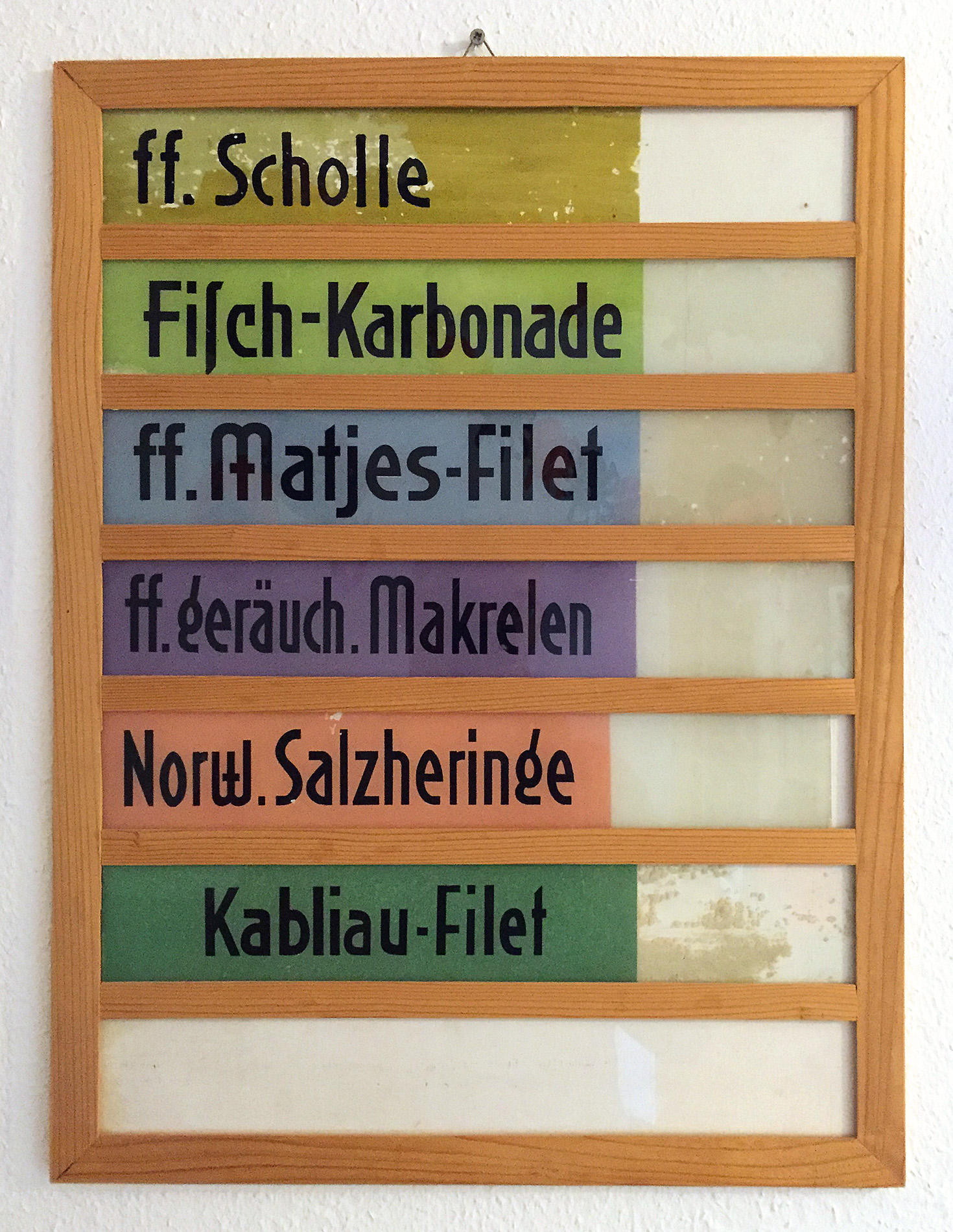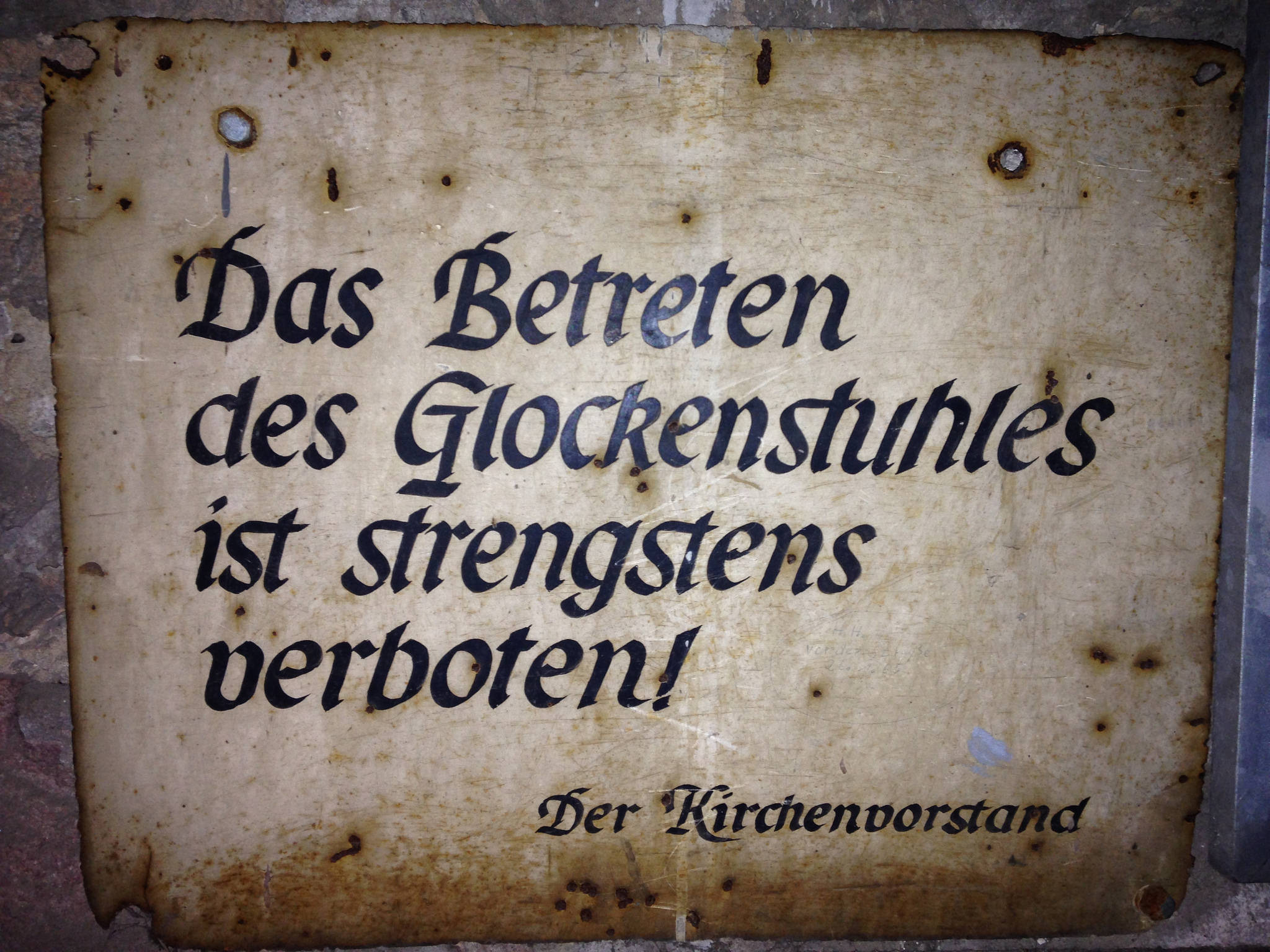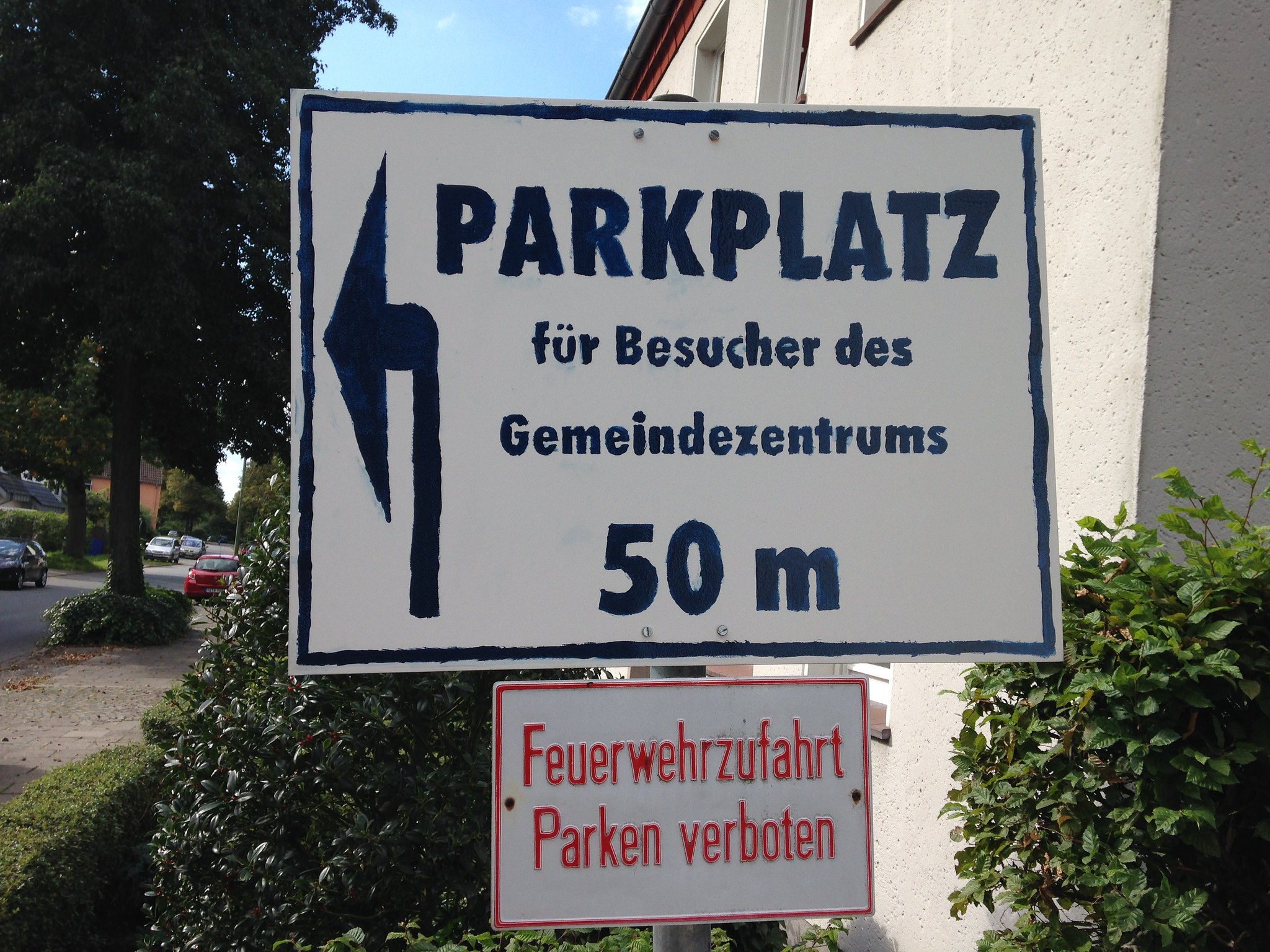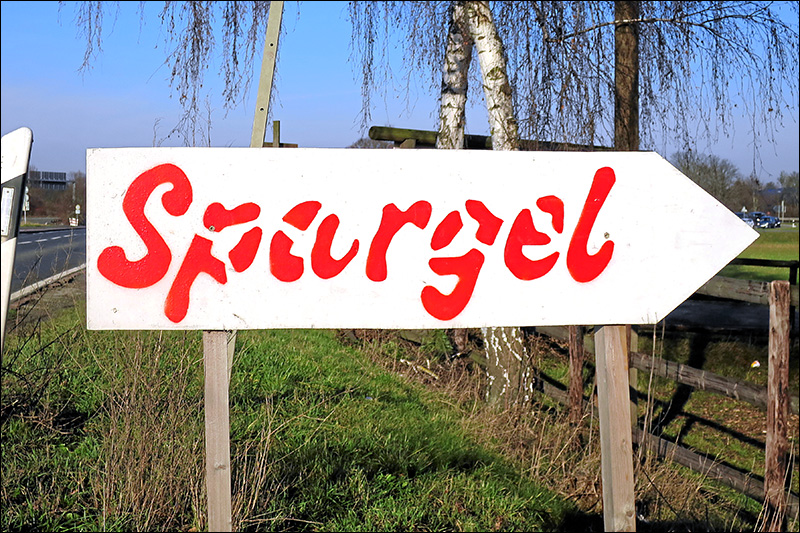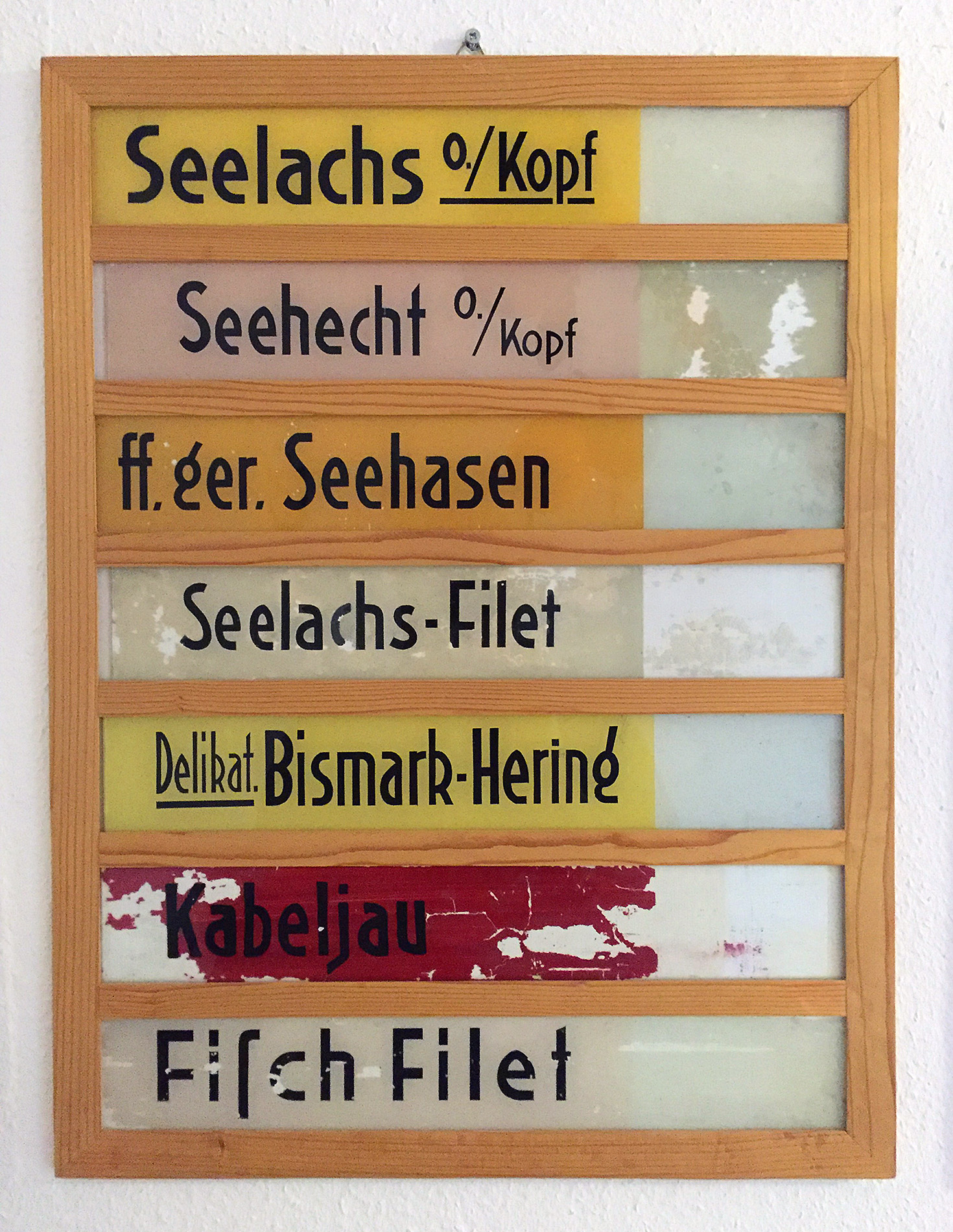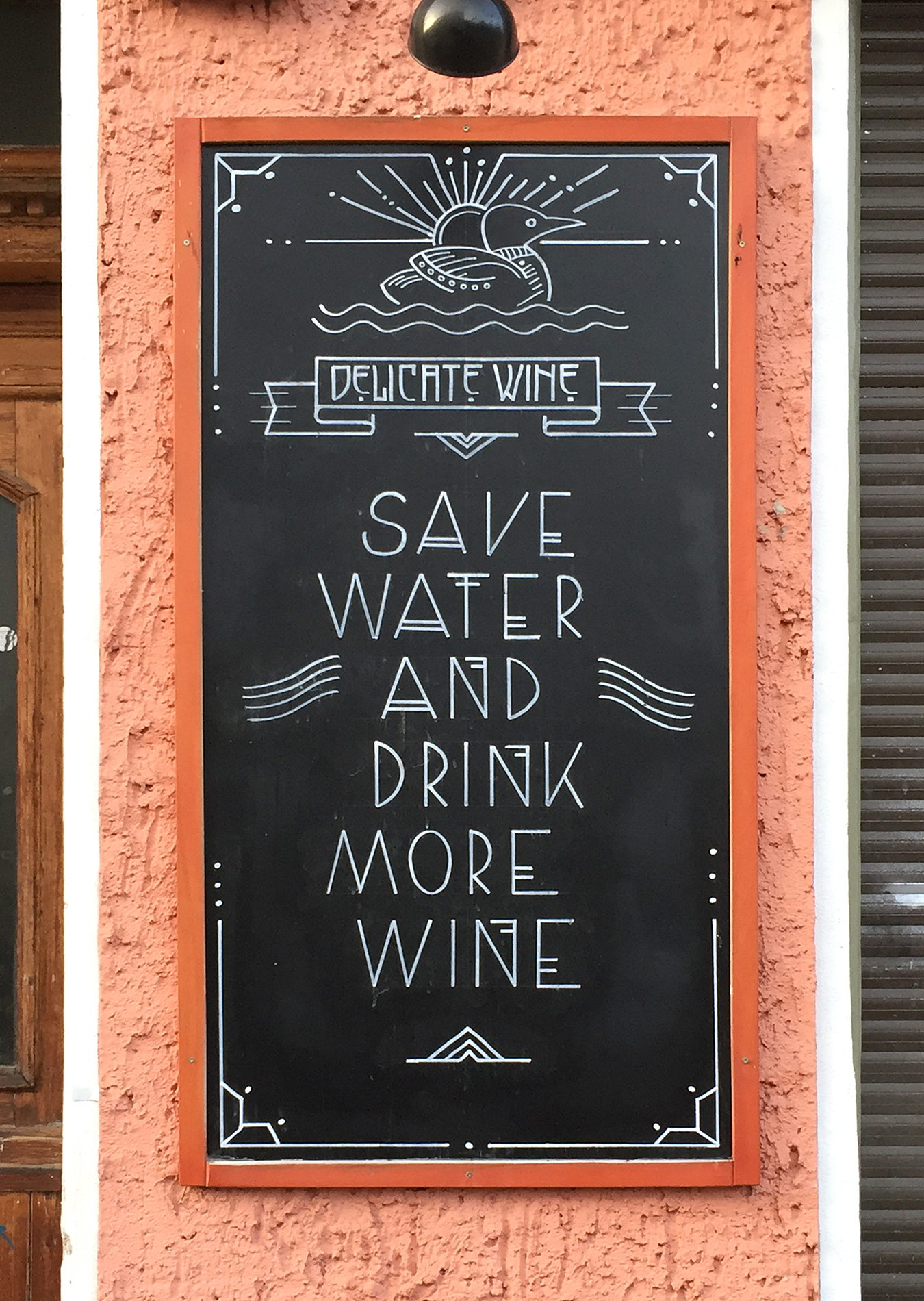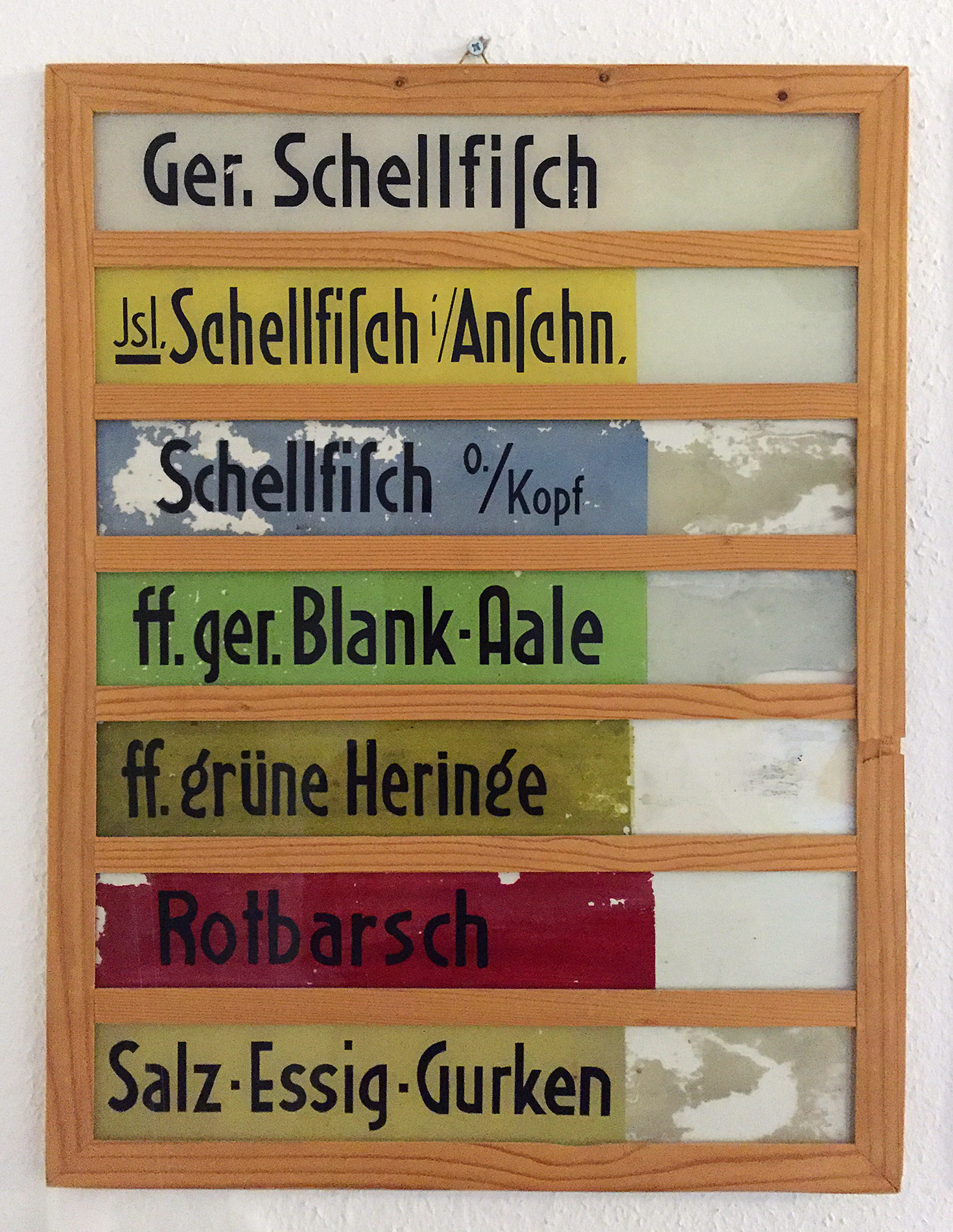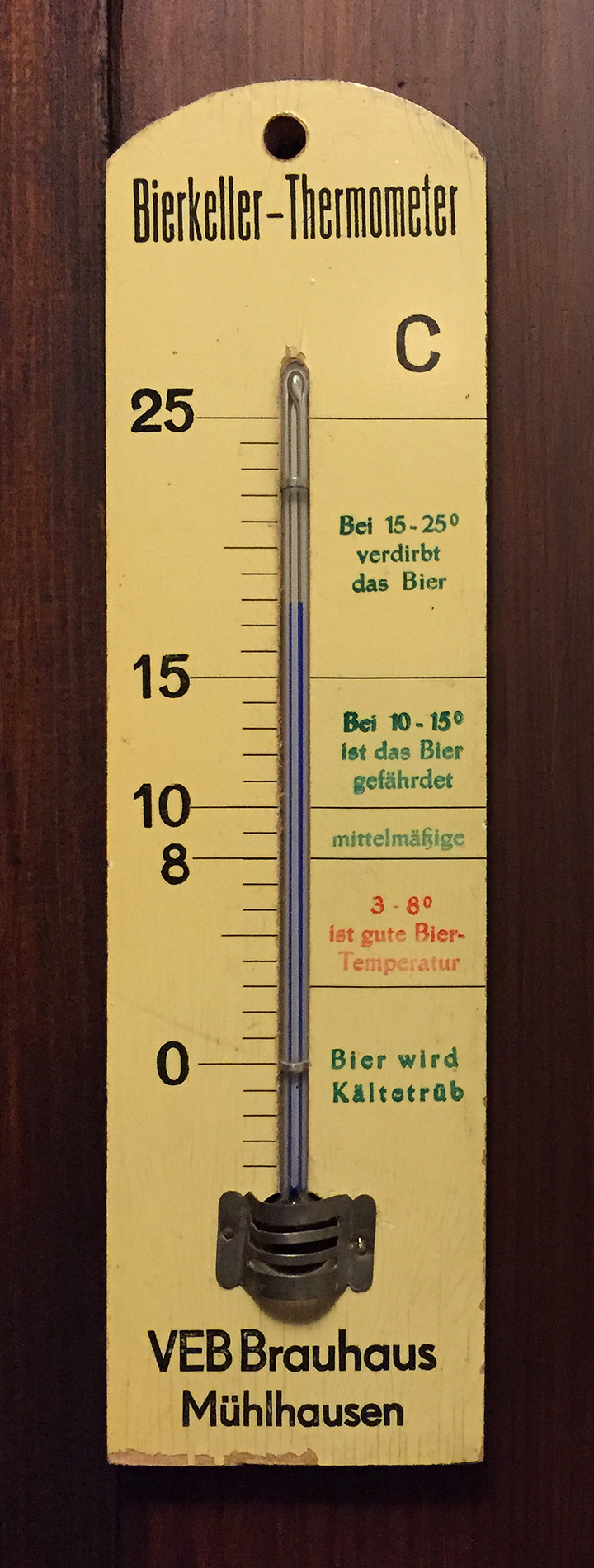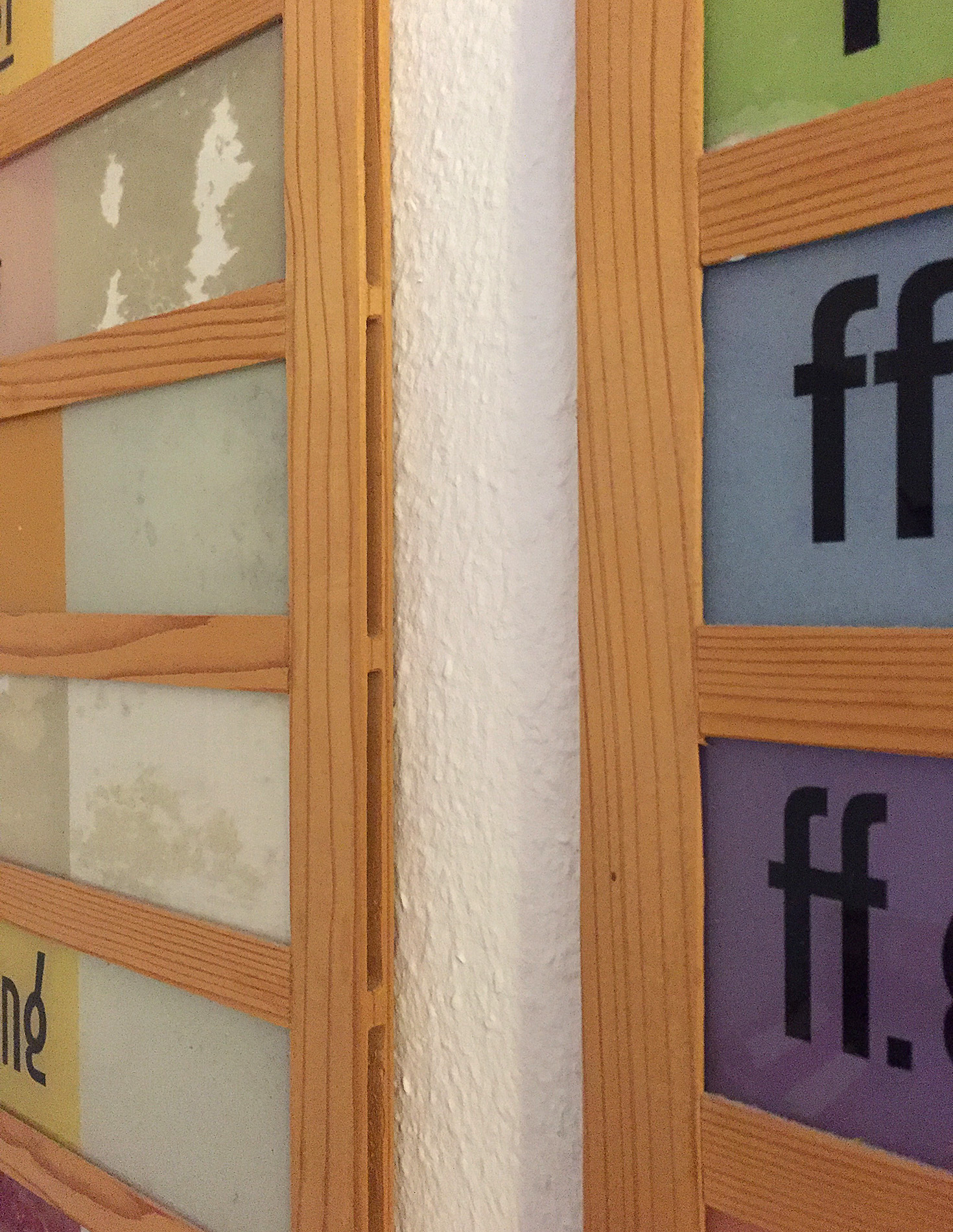
Hängt bei Freunden im Esszimmer - ein Kellerfund aus der Nachwendezeit. Die meisten Schilder dürften aus den 1920er- und 1930er-Jahren sein ...  :ilovetype:
Oh die sind ja schön!
Und toll finde ich auch die phantasievolle Schreibweise des Kabliau-Filets.
Darüber bin ich auch gestolpert. Allerdings scheint die Schreibweise durchaus mal gängig gewesen zu sein ...
Zwei Fundstücke aus Osnabrück, das zweite stammt aus dem Glockenturm von St. Marien.
Dazu passt:
was für erschreckende Öffnungszeiten. Die Vorstellung, ich könnte von Oktober bis April nichts zu lesen finden wäre für mich beinah schon tödlich.
Gesehen im Kaufpark Eiche (bei Berlin)
Das erste e hielt ich ja noch für einen Unfall eines Malers, der das Gleichgewicht auf der Leiter verloren hatte...
Vielleicht ist das Cafe für internationale Gäste, Hotel und Restaurant nur für conservative Deutsche?
Toller Trick, Übersetzungskosten zu sparen, nur hätten sie ein „Please write“ noch davor setzen sollen, damit die angesprochenen das auch kapieren. Ein Marker dort hinzupacken wär auch hilfreich.